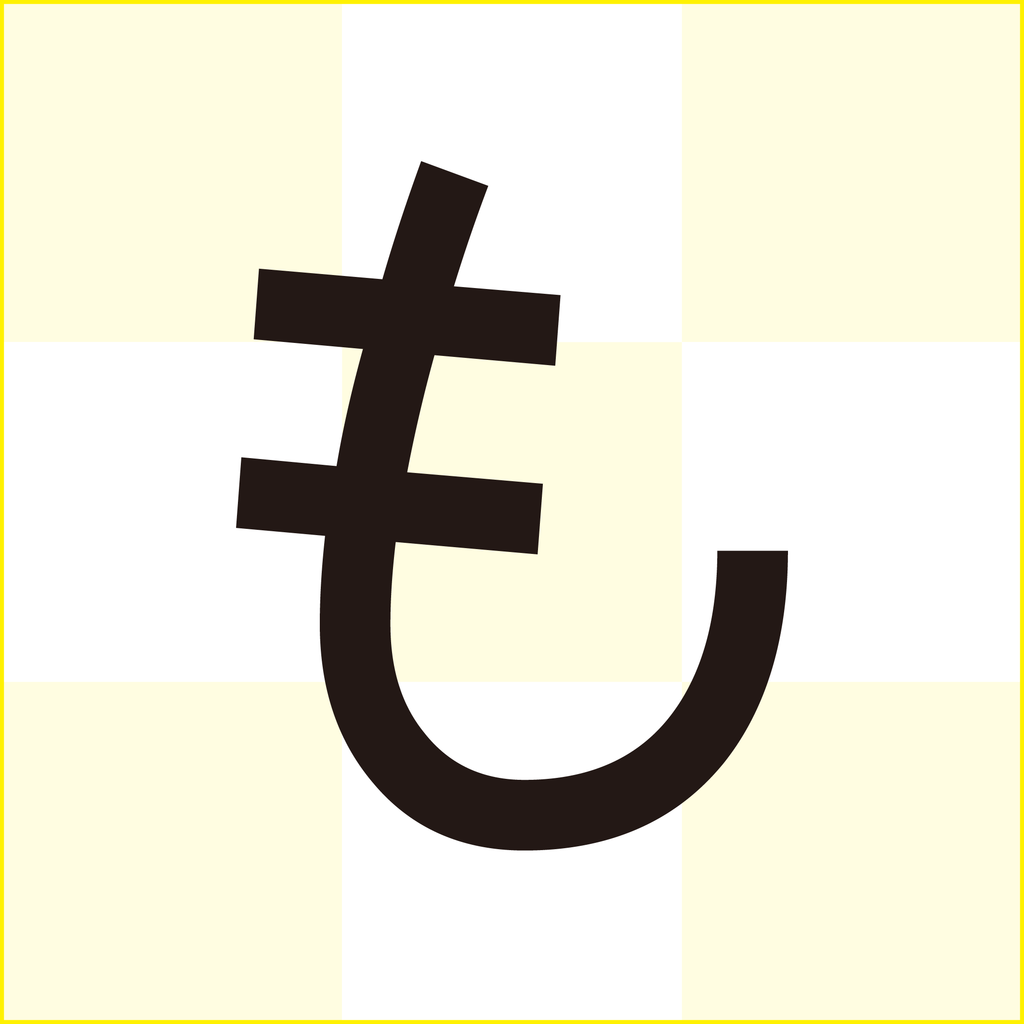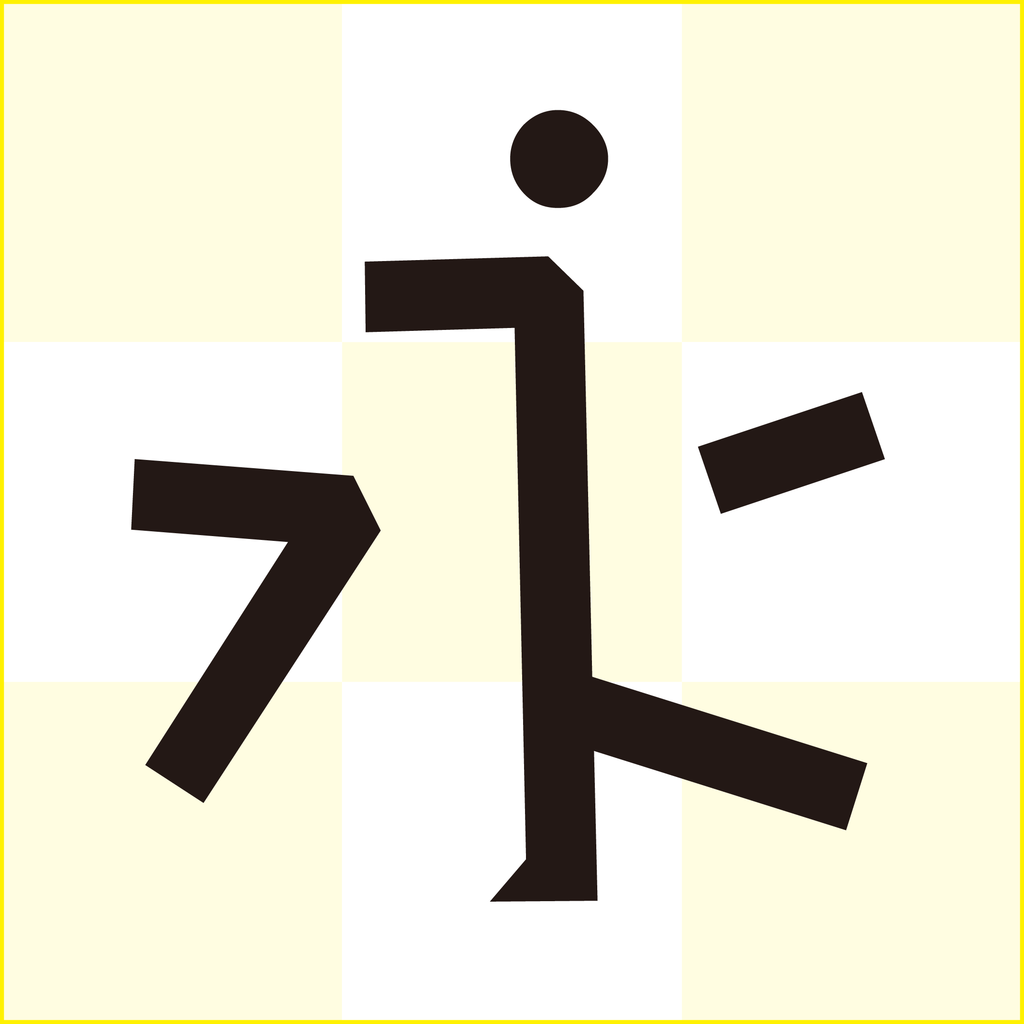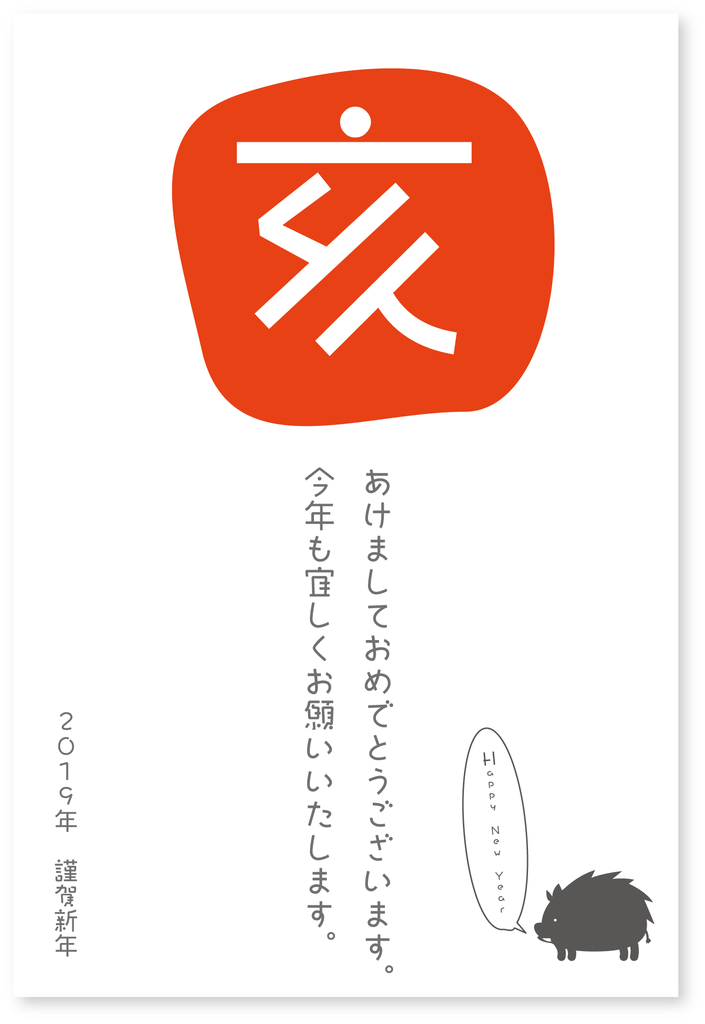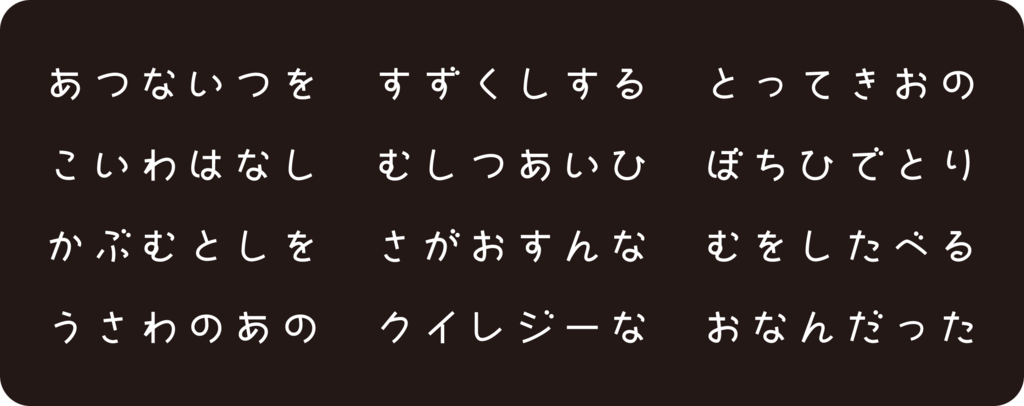
ナーティ
やや幅広のつくりにビー玉のように丸いデザインの点画と曲線を描いたようなはらいのフォント。ナーティ(naughty)はいたずら好きな、わんぱくなといった意味で、フォントのコンセプトもそんな感じらしい。
ナーティ 文字見本(W5)
ナーティはダイナコムウェアが開発・販売するダイナフォント(DynaFont)シリーズのフォント(書体)であり、有料フォントとなっている。